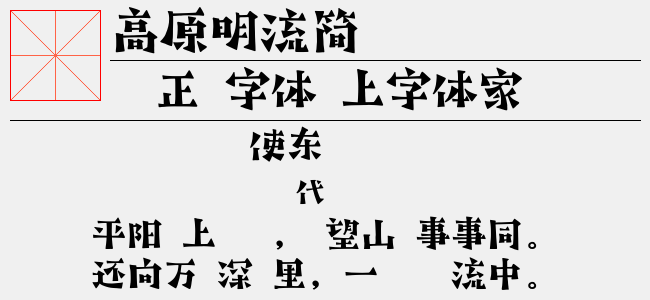
高原明流简 字体大小436.55 K,包含了6763个汉字以及附加其他英文字体和阿拉伯数字,属于极字和风字库。高原明流简(TTF)可以免费下载,商业用途请自行购买版权,它的特征就是个性,卡通,创意,海报,采用安装嵌入的安装方式,支持符号拉丁文日文中文等语言
字体作者:极字和风字库
字体名称:高原明流简